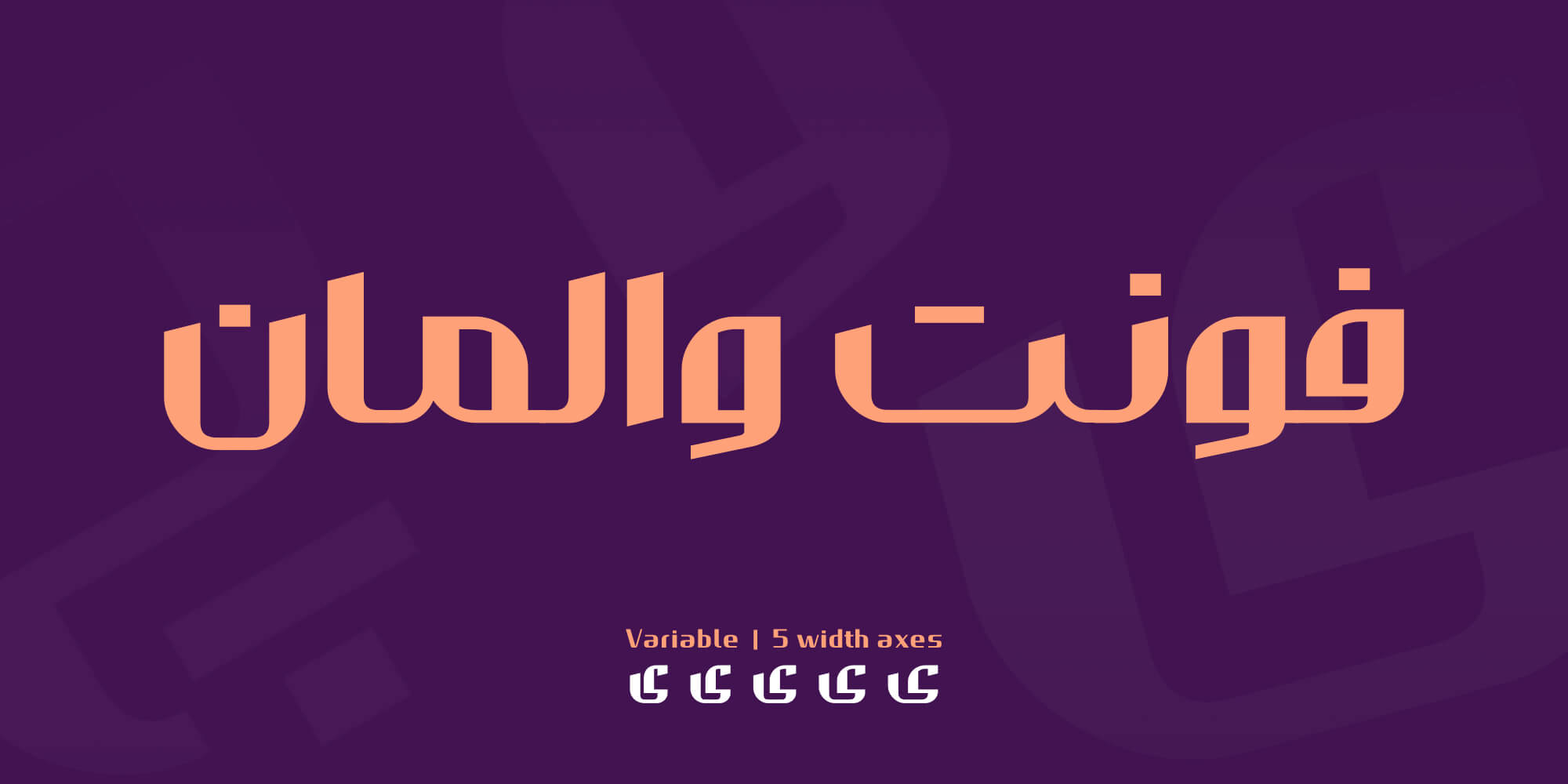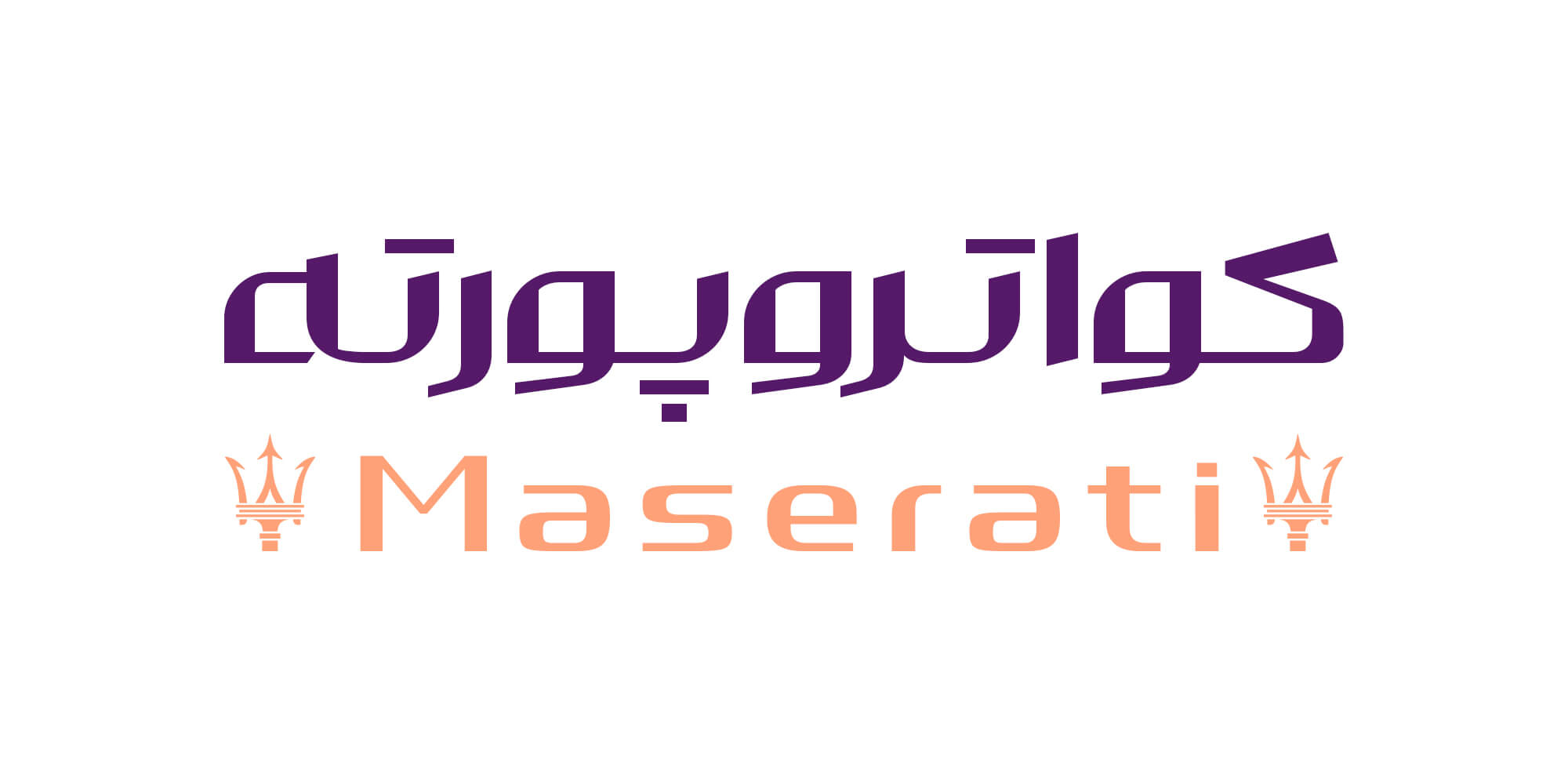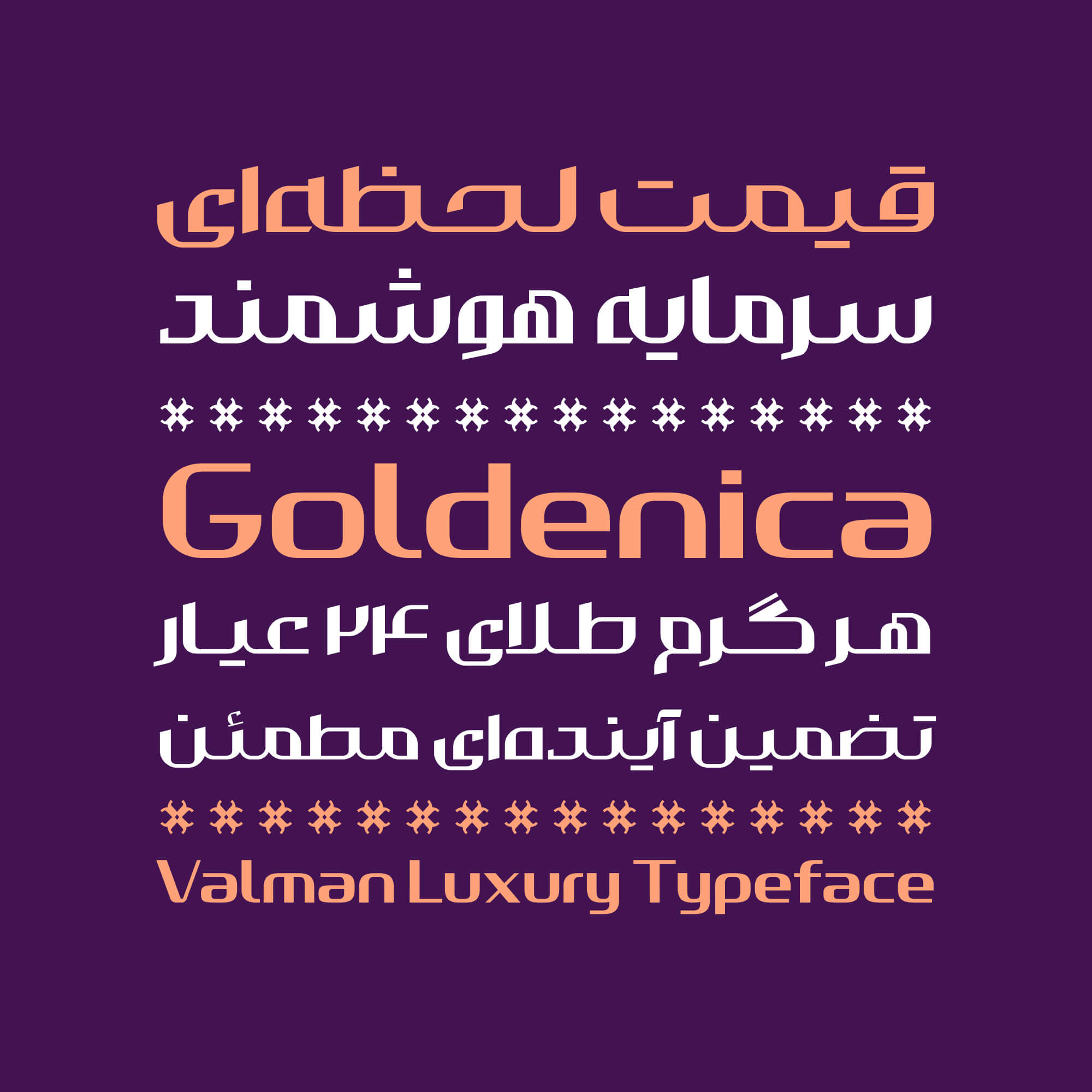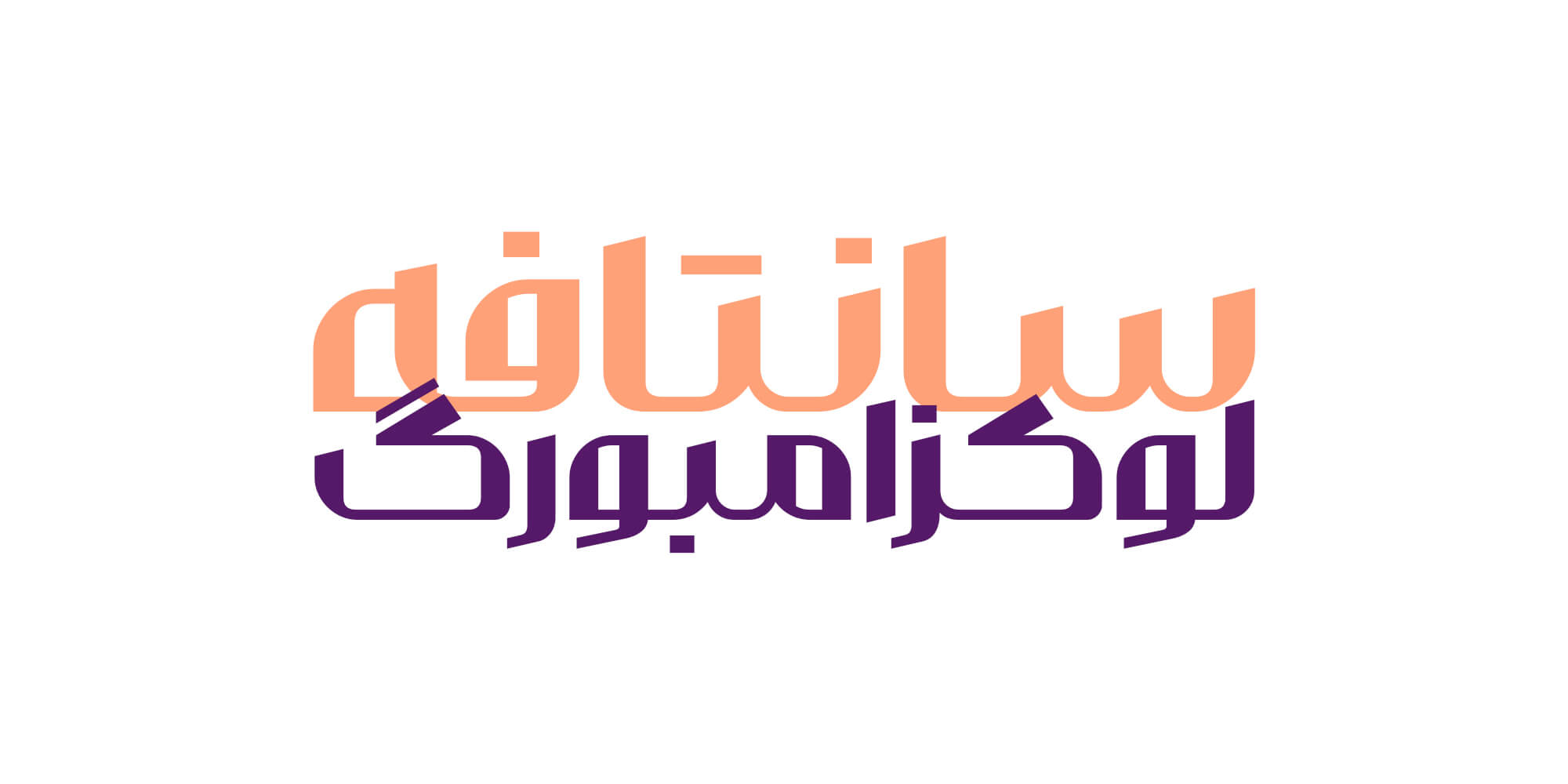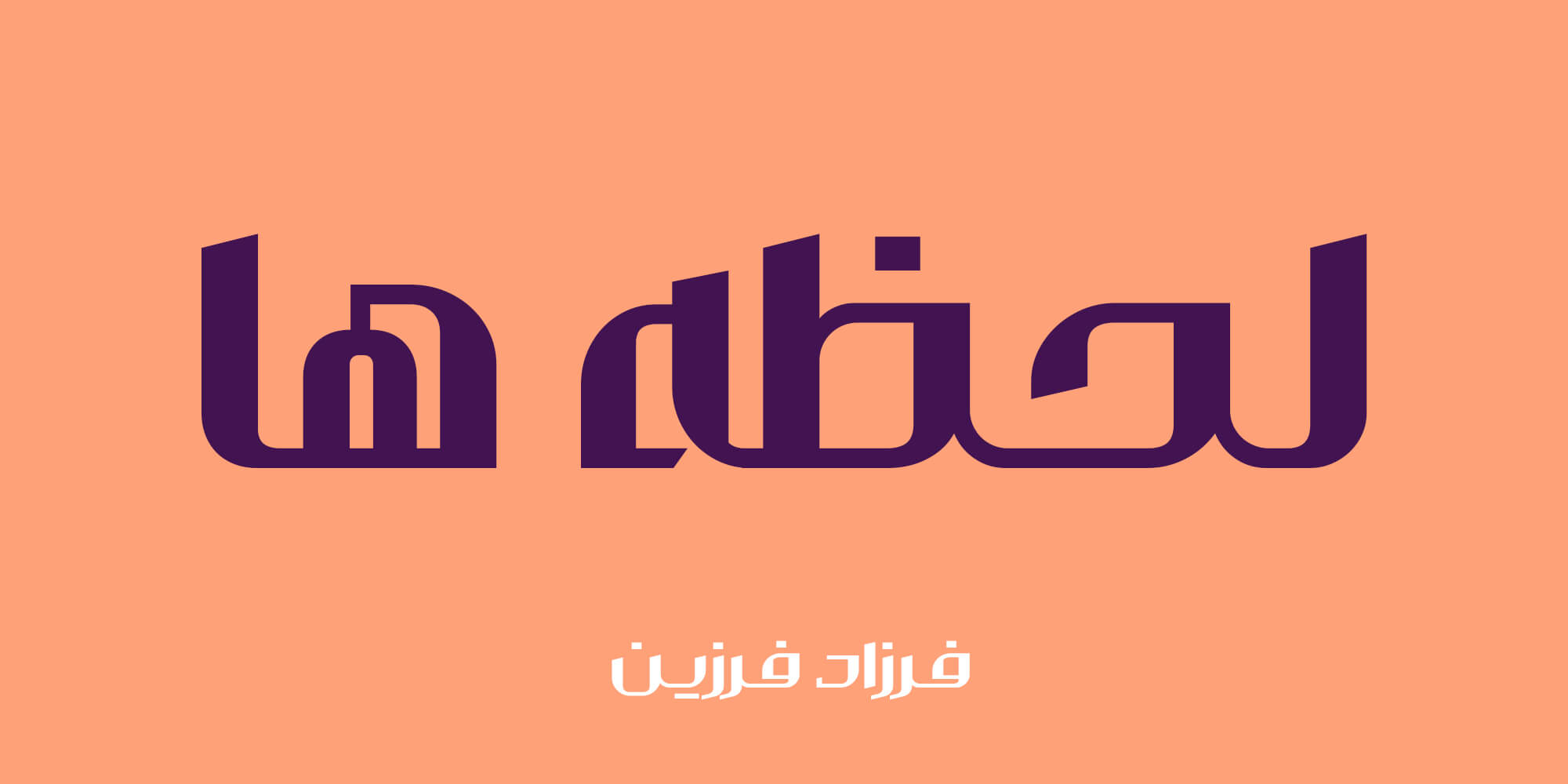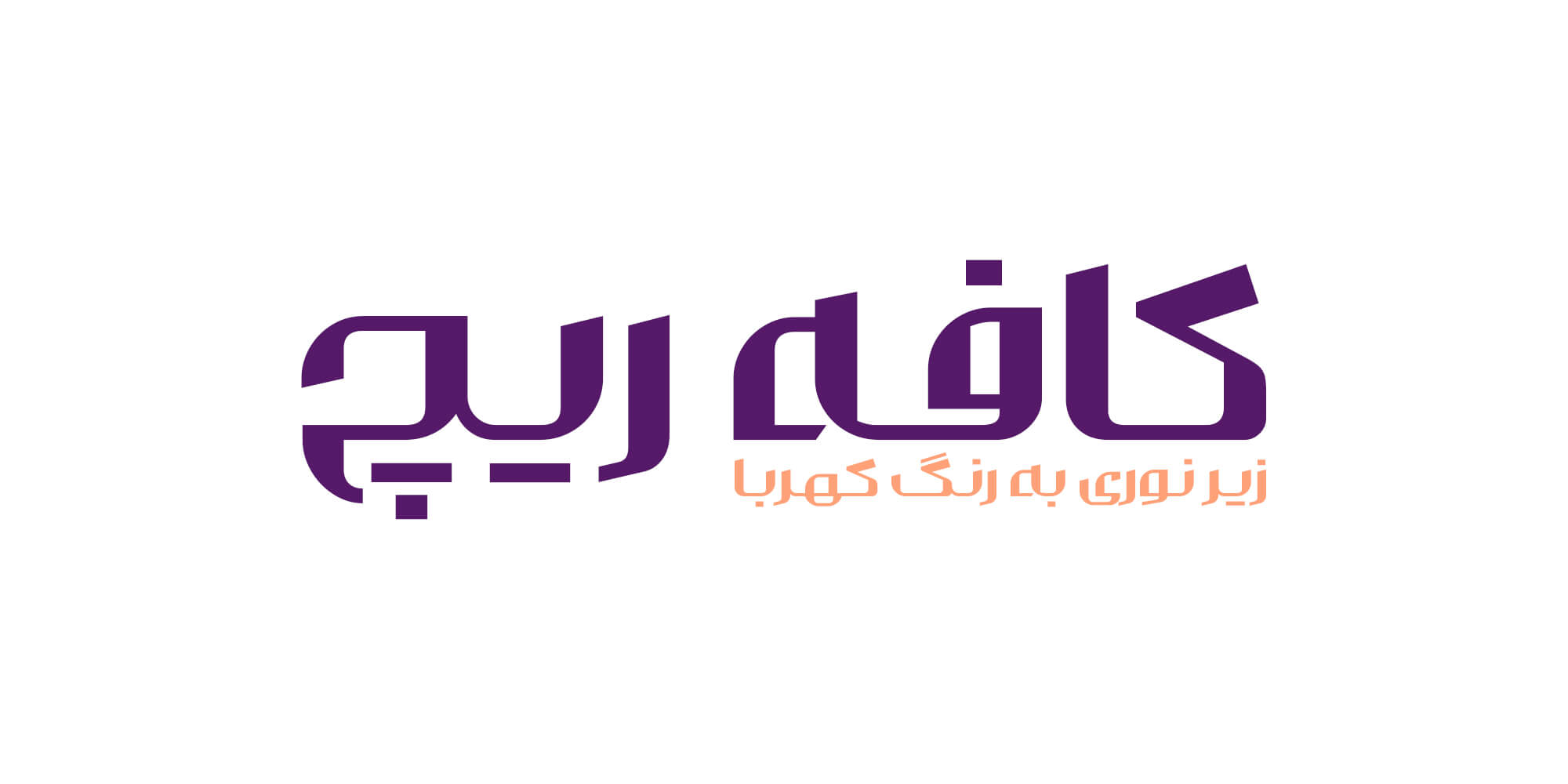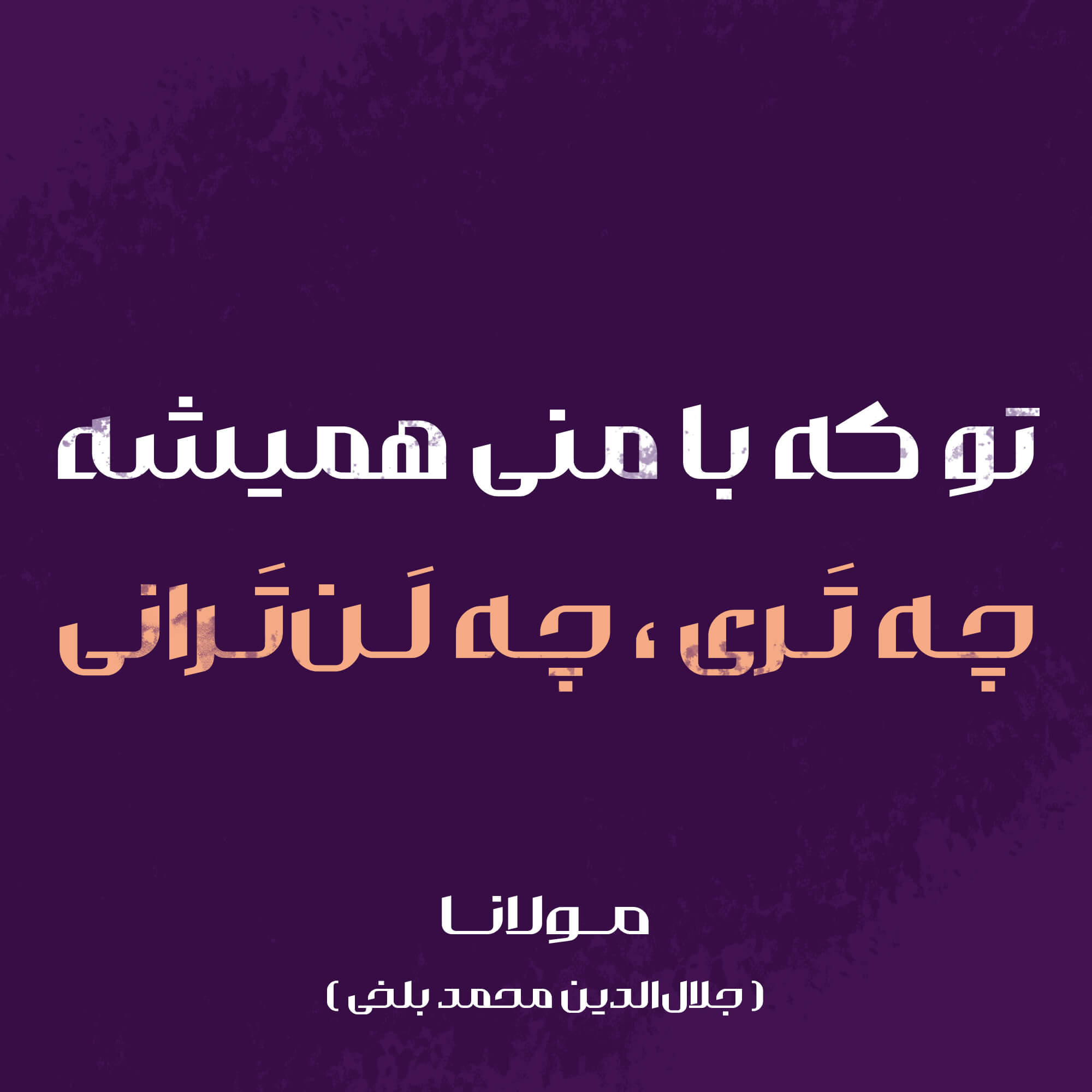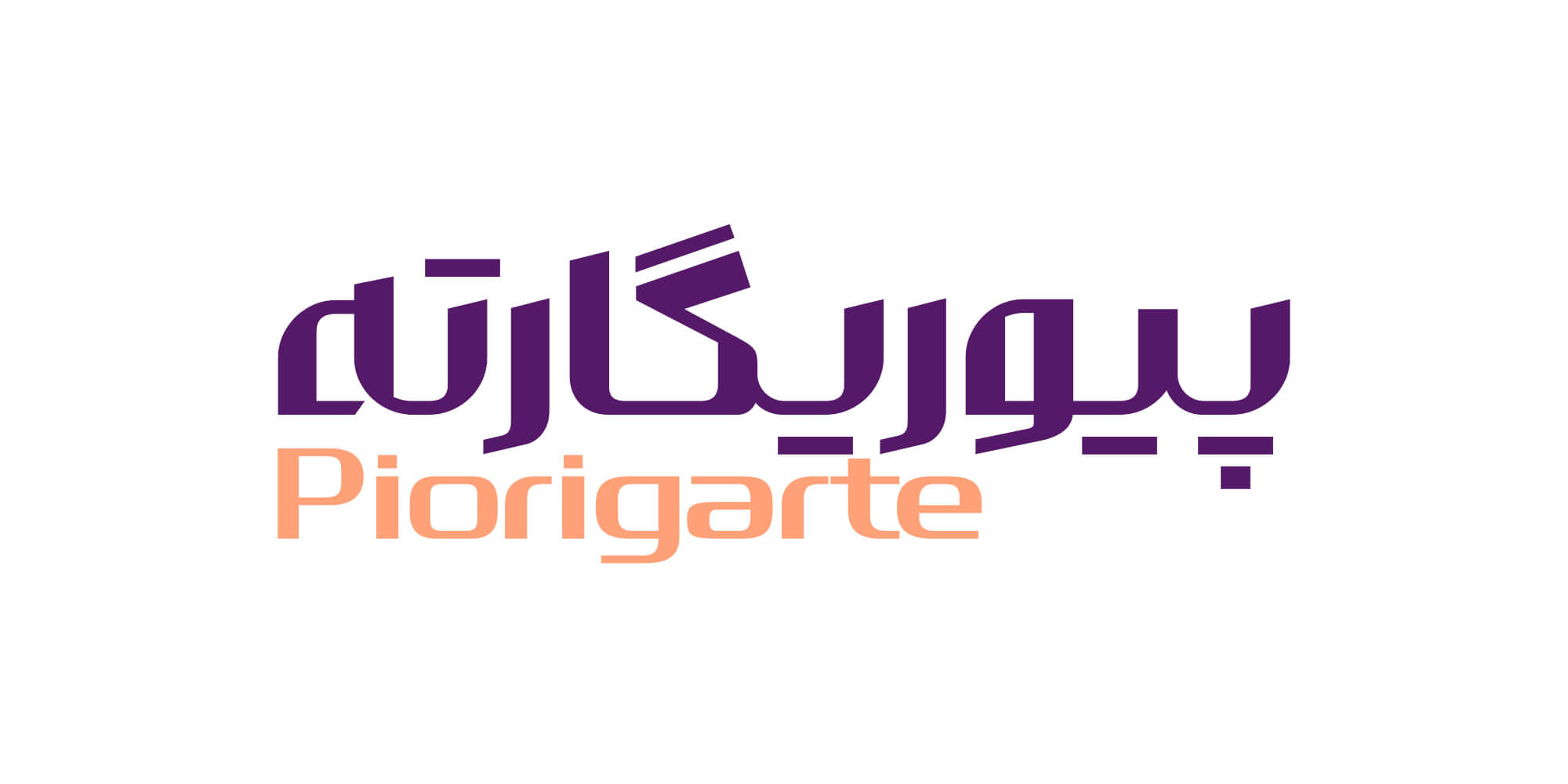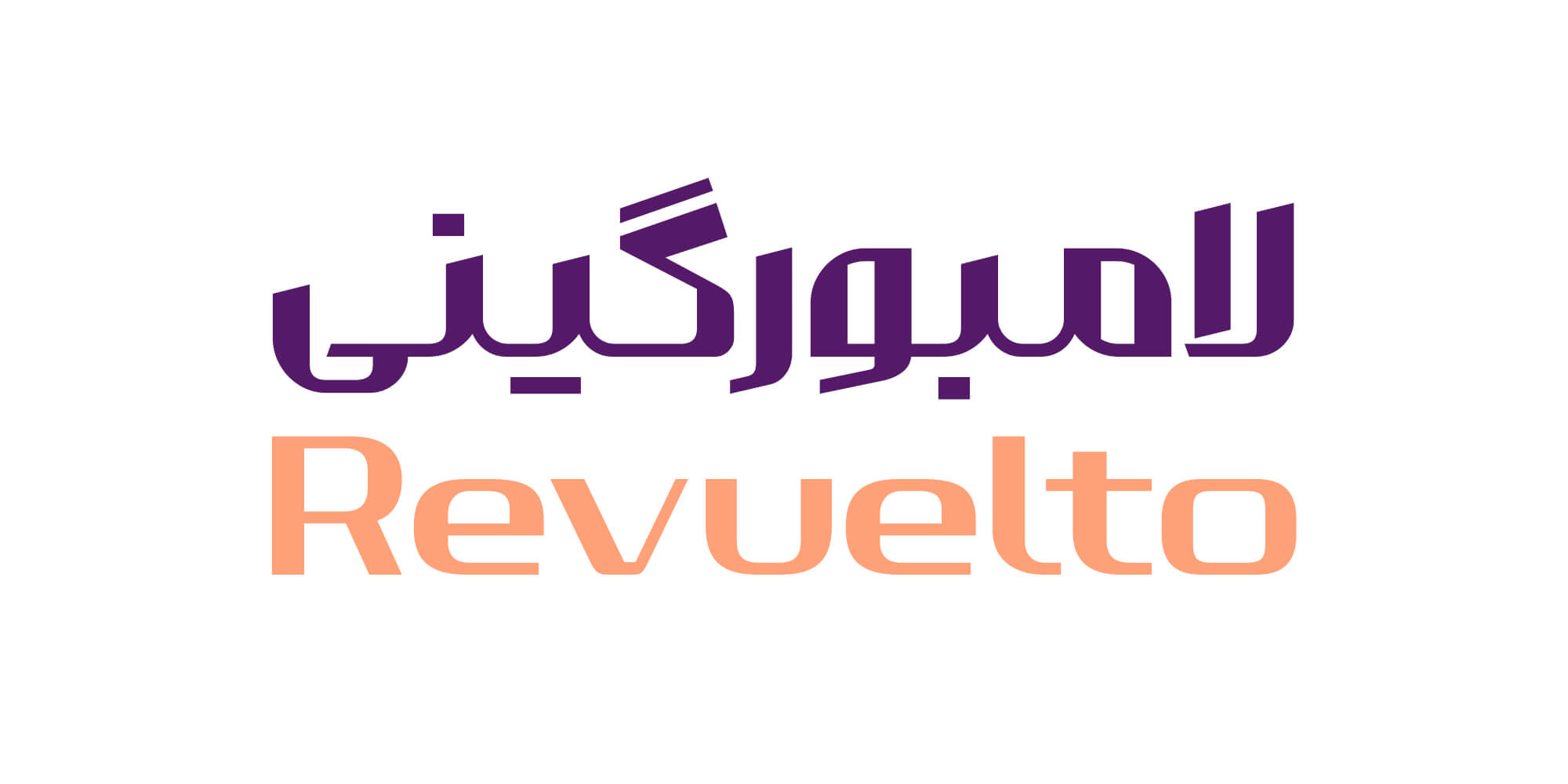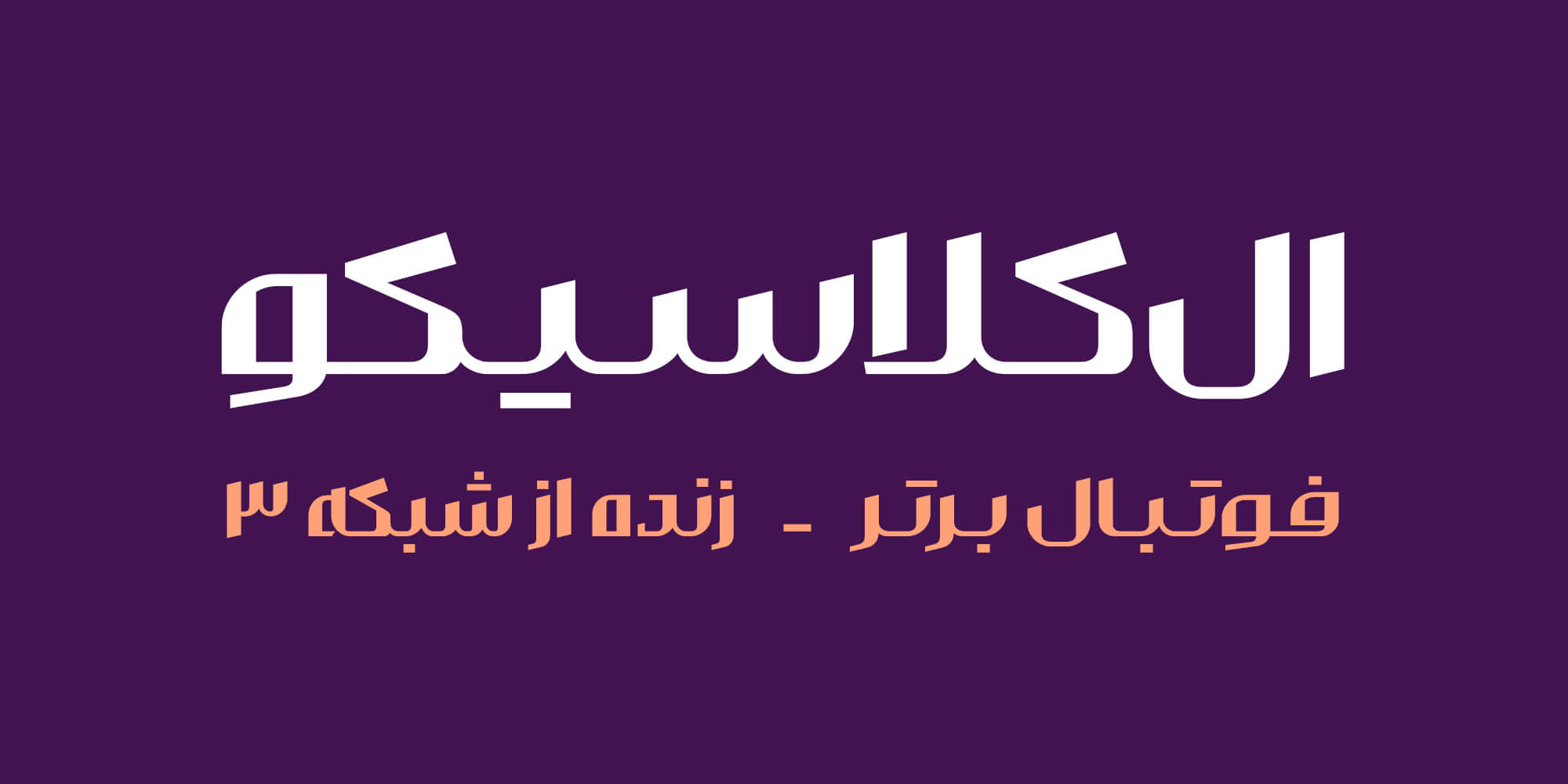
فونت والمان کار شما را برای طراحی لوگوتایپ آسان می کند.
همچنین از فونت والمان میتوانید در طراحی بسته بندی، تابلو فروشگاه و انواع تبلیغات تجاری که میخواهید لوکس و مدرن به نظر برسد استفاده کنید.
5 سطح عرضی مختلف ؛ از فشرده تا گسترده
نمادهای پول ؛ طراحی نماد ریال و تومان!
در فونت والمان شکلهای خلاصه شده و نمادهای پیشنهادی برای ریال و تومان وجود دارد.
ترکیبات، لگیچرها و حروف جایگزین
زبانهای پشتیبانی شده در فونت والمان
فونت والمان از زبانهای فارسی ، عربی، اردو، کوردی و جاوی پشتیبانی میکند.
اعداد و علائم در فونت والمان
. شامل اعداد فارسی، انگلیسی و عربی
. شامل اعداد همعرض
. شامل اعداد پایین رونده (مناسب الاین کردن در کادرها و فضای درج قیمت در دکمه سایتها و بنرهای مربوط به لیست قیمت)
وریبل فونت والمان
استفاده از وریبل فونت در طراحی وب روز به روز رایجتر میشود. فونت متغیر امروزه در بسیاری از سایتهای پربازدید فارسی در حال استفاده است.